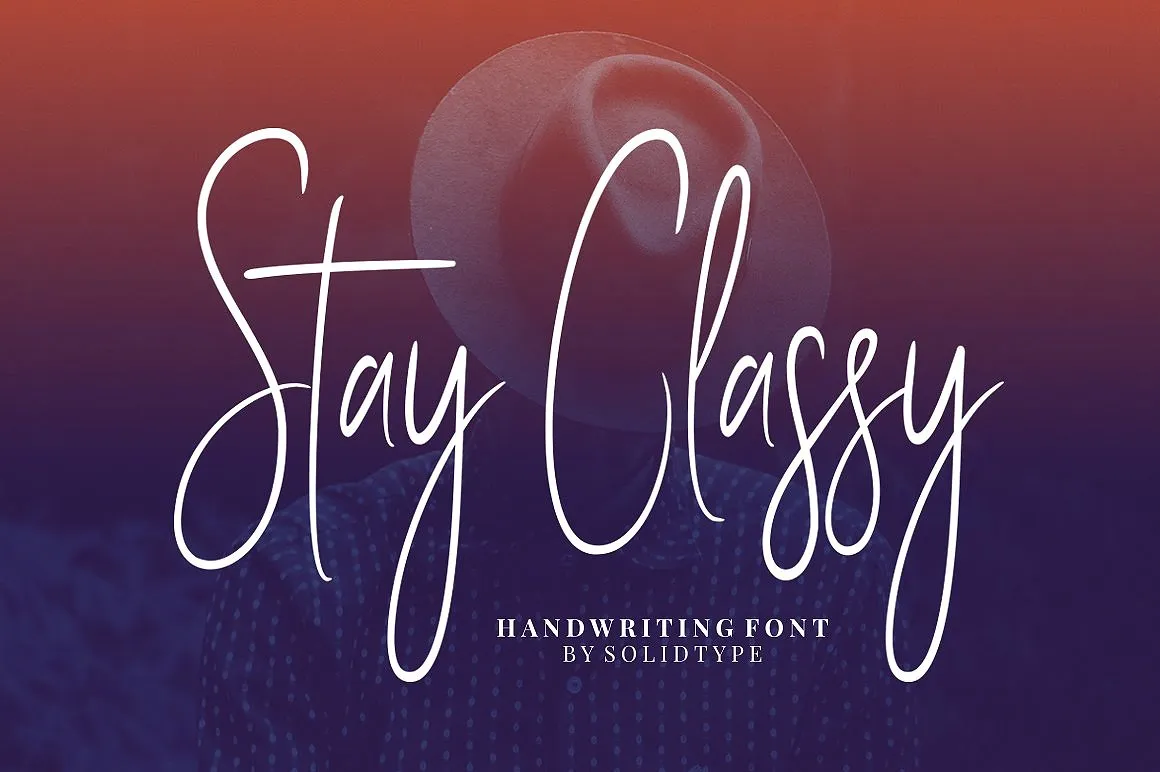
Stay Classy Script Font – Download Grátis
A nova “Stay Classy” Script Font vem de Hamilton, designer responsável por essa elegante tipografia escrita a mão, adequada para múltiplos projetos. Desenvolvida pela Solidtype, esta font proporciona um estilo gráfico moderno e sofisticado ideal para diversos usos, incluindo blog, redes sociais, marcação de eventos, cartões de aniversário, e muito mais. Com sua escrita elegante e fashionista, “Stay Classy” Script é uma excelente escolha para aqueles que buscam um tom único em seus projetos digitais. Perfect para qualquer projeto onde desejar ser inovador sem sair da estética clássica e sofisticada. Seja para blogs modernos ou cartões de aniversário criativos, esta font oferece uma maneira de manter a elegância em todos os seus trabalhos.